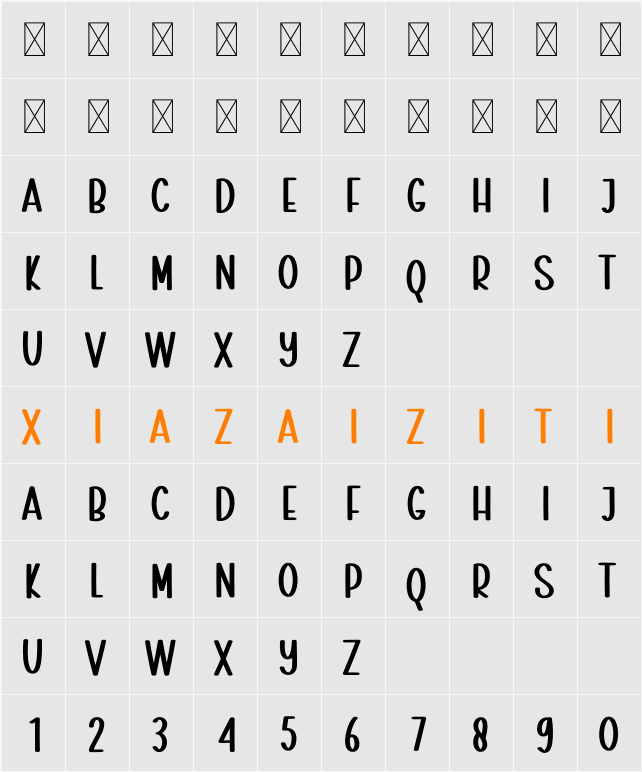
Workshop
Workshop,这款字体结构工整、笔画清晰,兼顾美观与易读性,适用于标题、正文、海报、包装、LOGO 等多种场景。字形优雅稳定,风格百搭耐看,适配日常排版与创意设计,让文字呈现更舒适、更具质感。Workshop一笔一画,皆是细节,以均衡的比例、流畅的线条打造舒适视觉体验,字形端正大气,风格简约现代。无论是商业设计、品牌宣传还是日常排版,都能轻松驾驭,让文字更有格调与力量。Workshop字体下载。